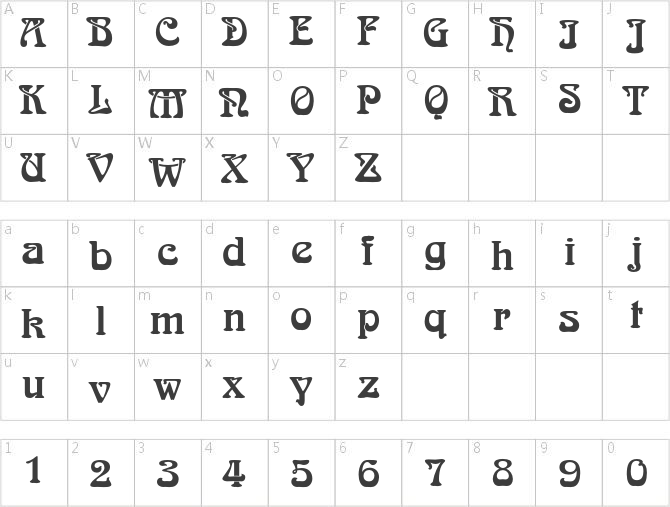
Arnold Boecklin Std
Arnold Boecklin Std介紹
Arnold Boecklin Std字體ArnoldBoecklin字庫是一款讓人賞心悅目、百看不厭的英文字體,適合各類廣告和產品包裝設計應用,字體大小0.04MB,格式為otf字體,上傳用戶是Who am I?,作者/版權方為Adobe